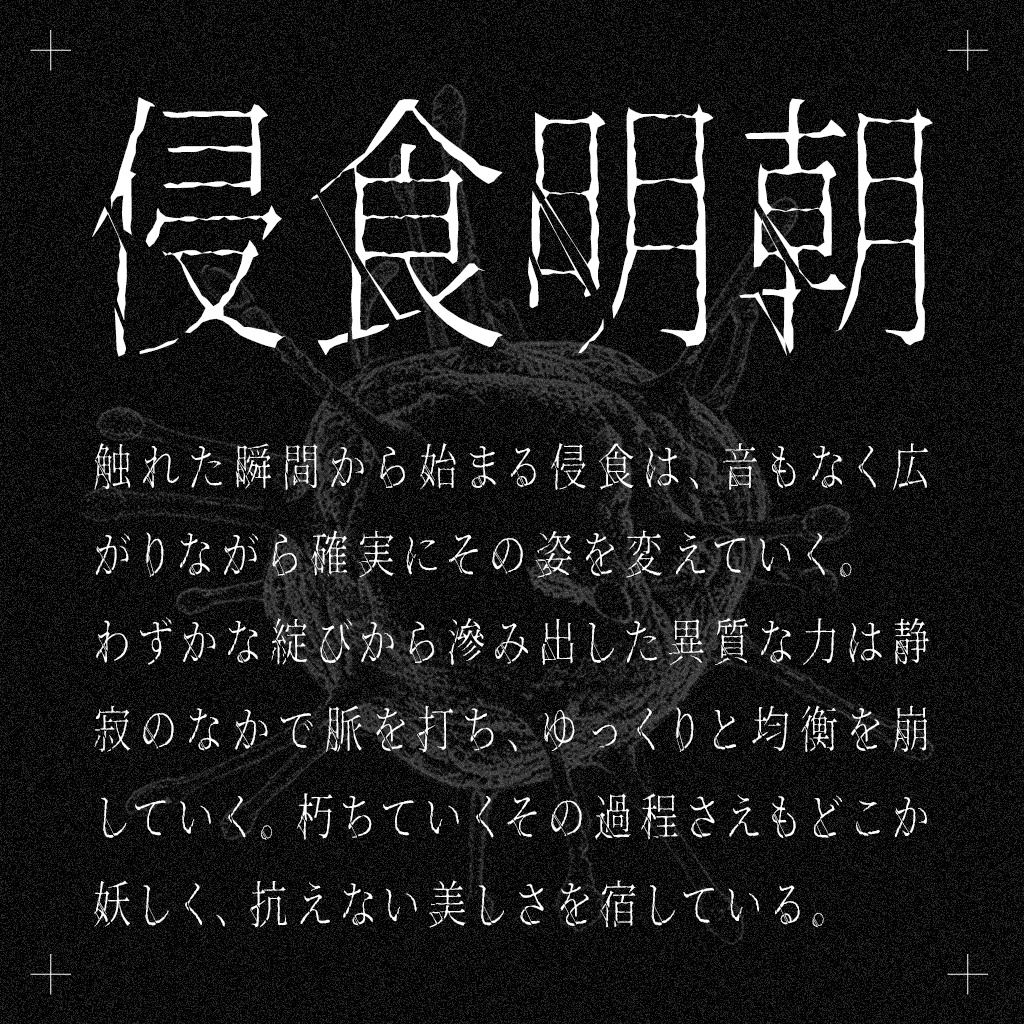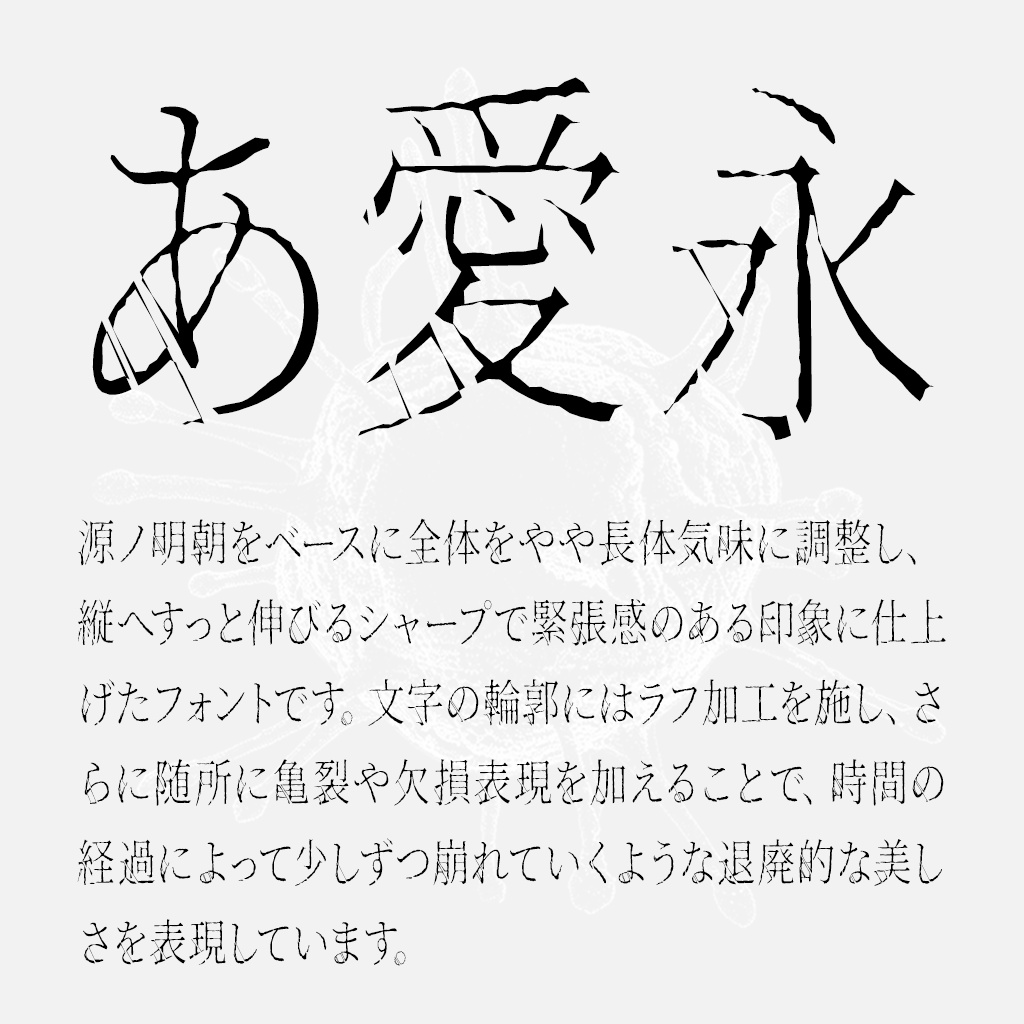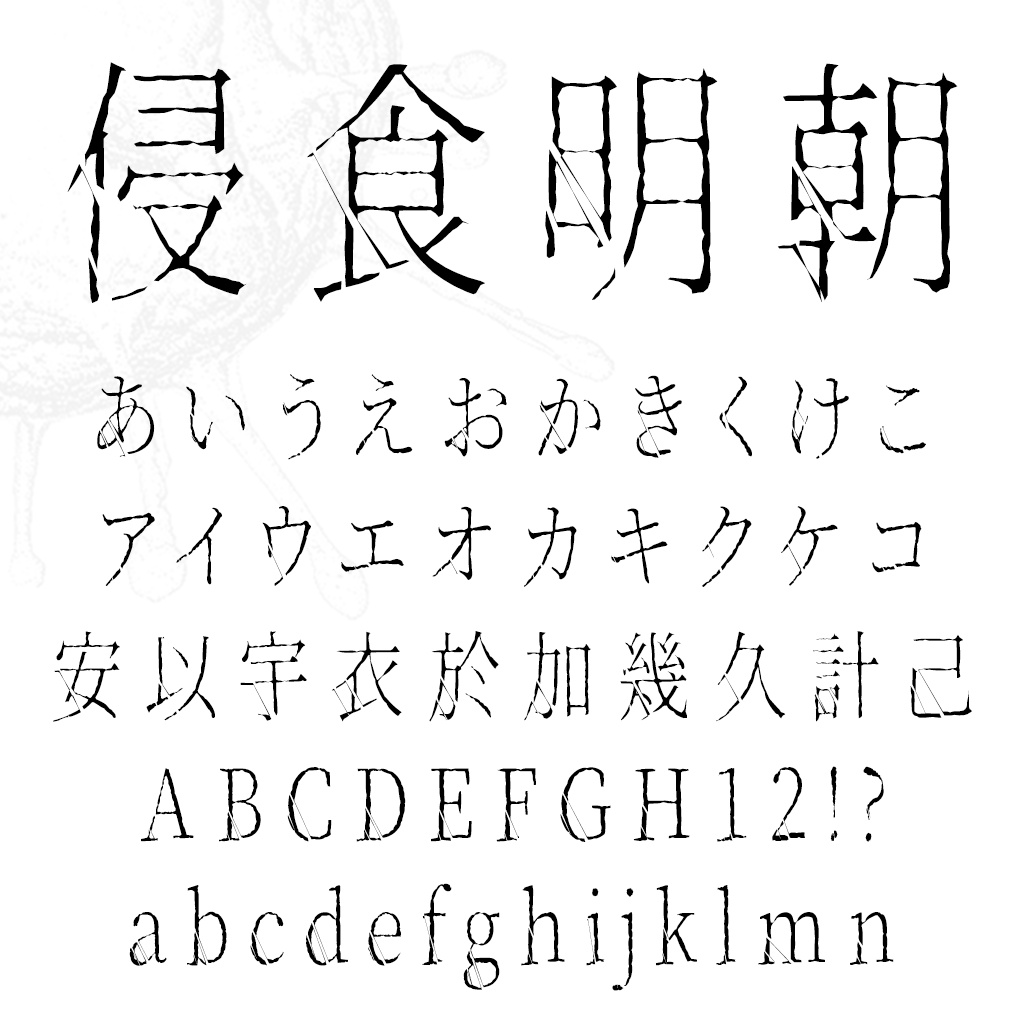
侵食明朝(フリーフォント)
【概要】 侵食明朝は、源ノ明朝をベースに全体をやや長体気味に調整し、縦へすっと伸びるシャープで緊張感のある印象に仕上げたフォントです。文字の輪郭にはラフ加工を施し、さらに随所に亀裂や欠損表現を加えることで、時間の経過によって少し侵食され崩れていくような退廃的な美しさを表現しています。 無料版と投げ銭版(¥500)のフォント内容は同一です。 【ライセンス・規約について】 このフォントはSIL Open Font License 1.1で公開されています。 個人・商用にかかわらず無償で使用可能で、動画・サムネイル・ゲーム等への組み込みなどご自由にご利用ください。 詳しいSILライセンスについてはサイトをご確認ください。 https://licenses.opensource.jp/OFL-1.1/OFL-1.1.html 当フォントを利用して発生した、いかなる損害についても作者は責任を負いません。 フォントデータをダウンロードした時点で利用規約に同意したものとみなします。 【改変元フォント】 源ノゴシック/源ノ明朝/Noto Sans/Noto Serif 関係者に深くお礼申し上げます。 【アップデート】 2026/07/02《ver1.000》リリースしました ========= 崩れなどございましたら、お知らせいただけますと幸いです。